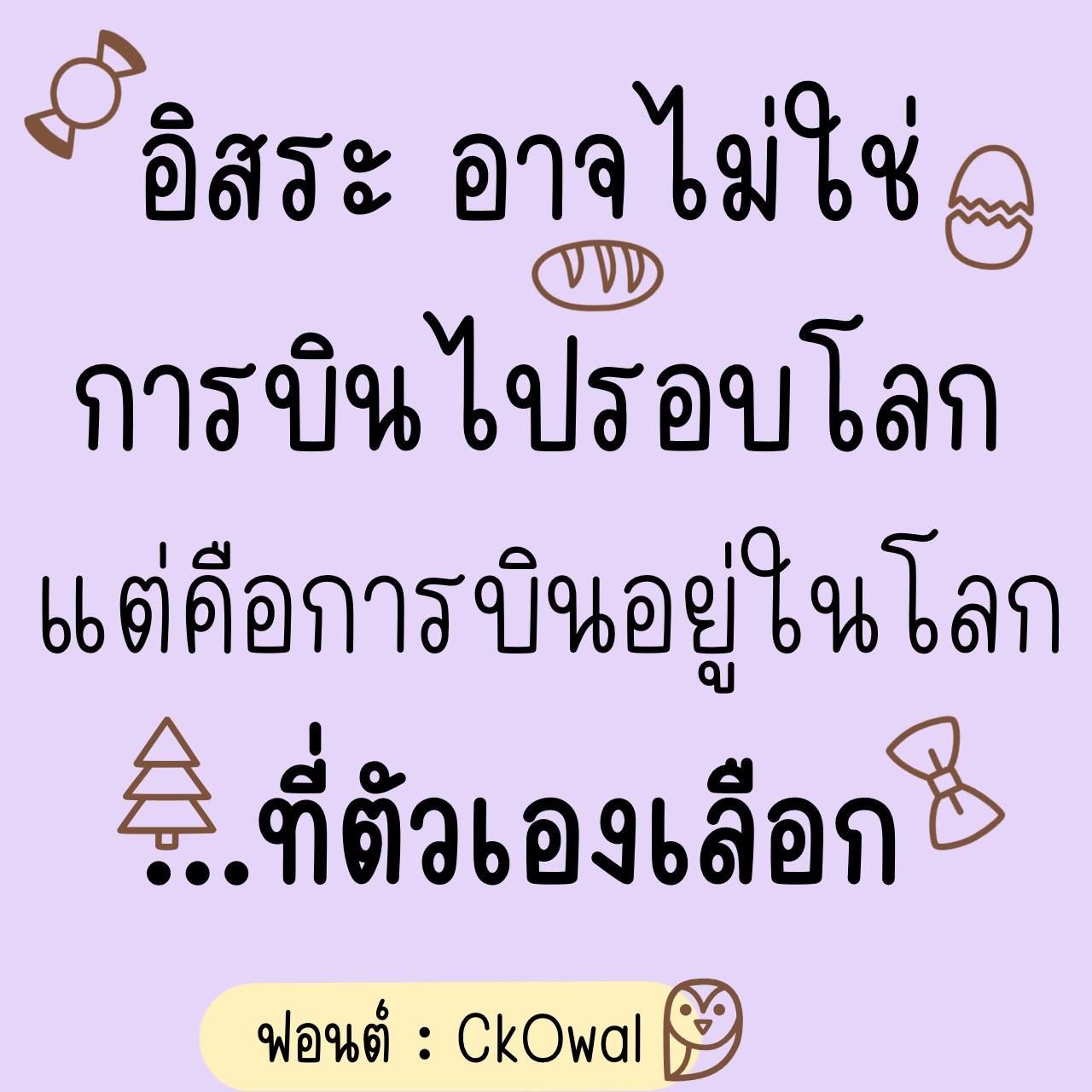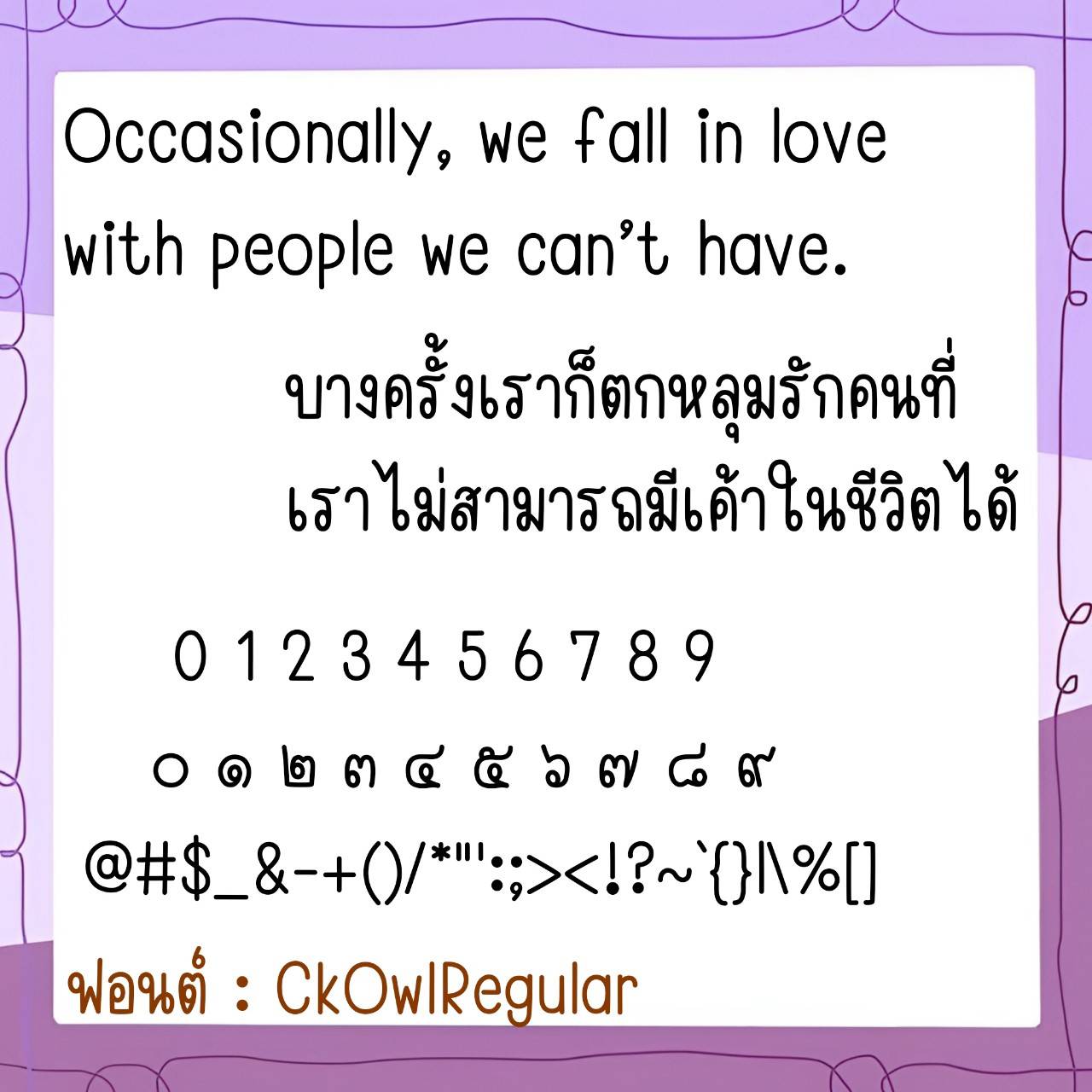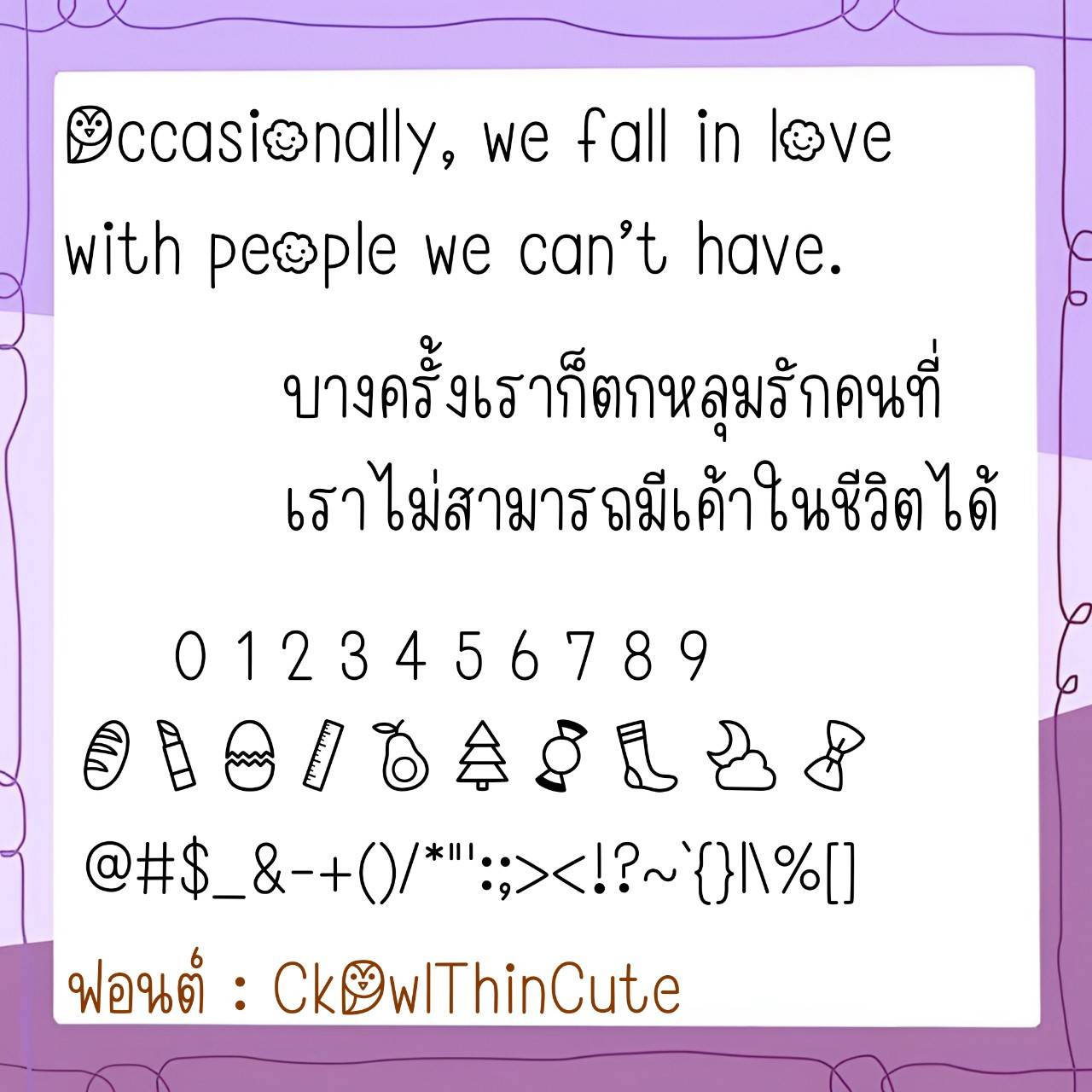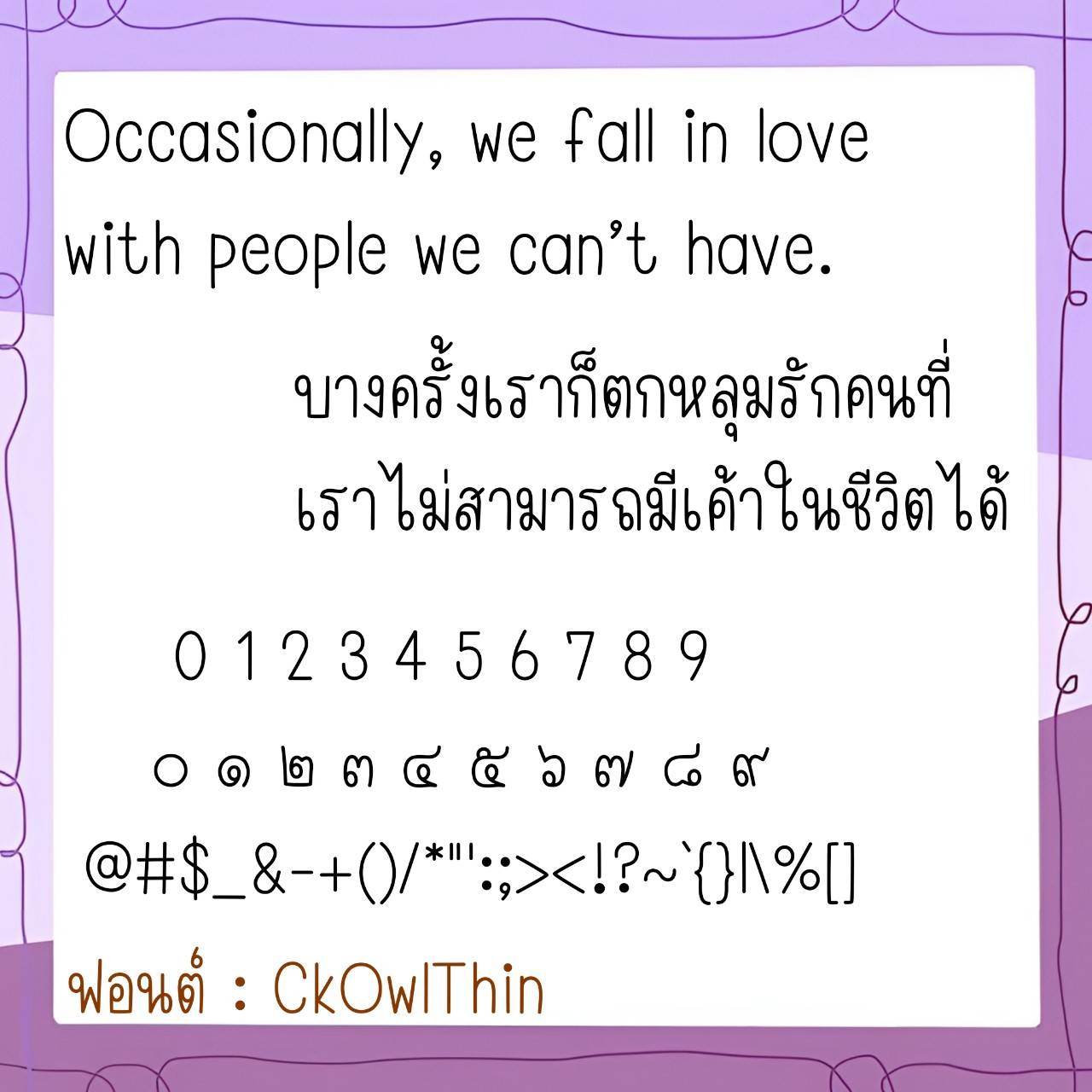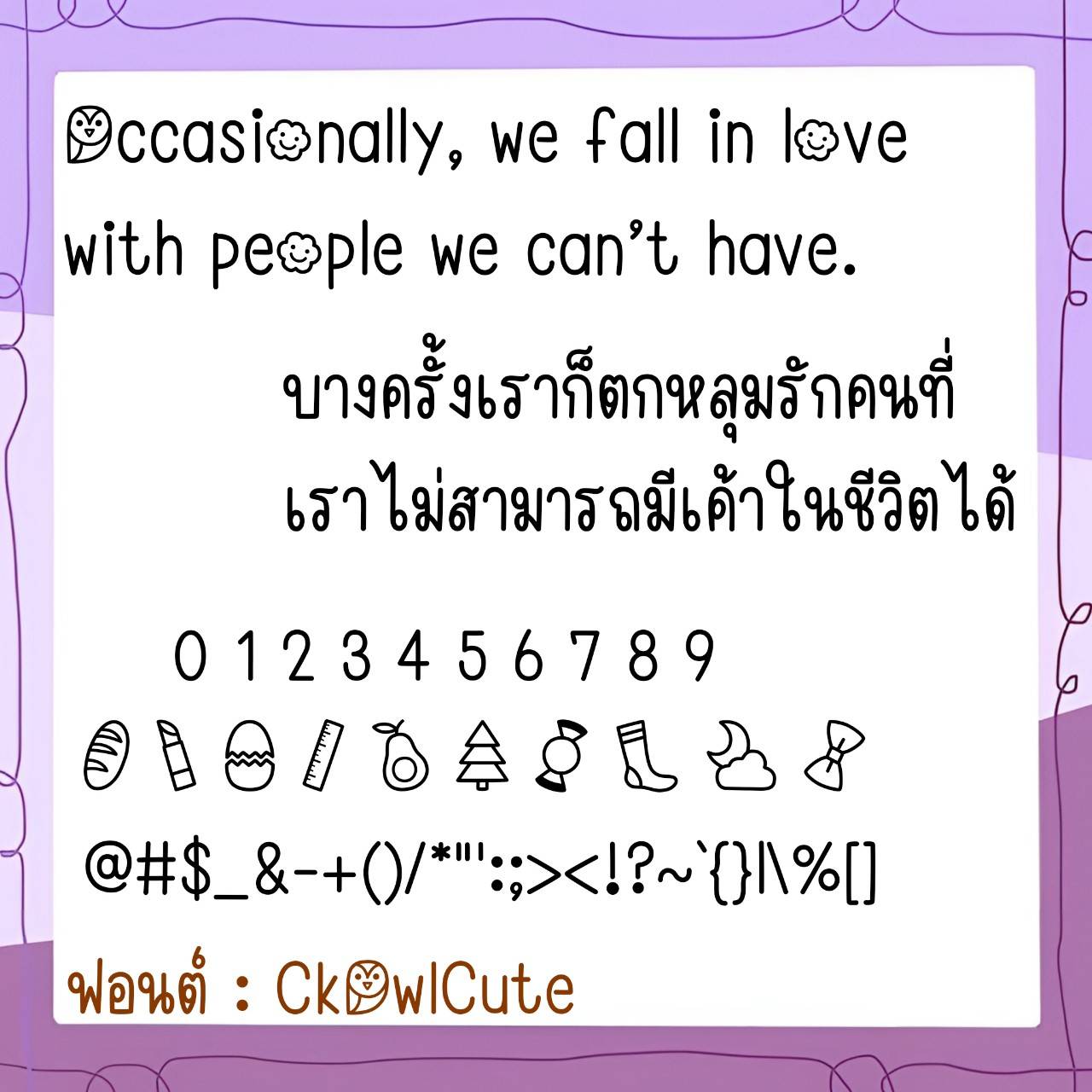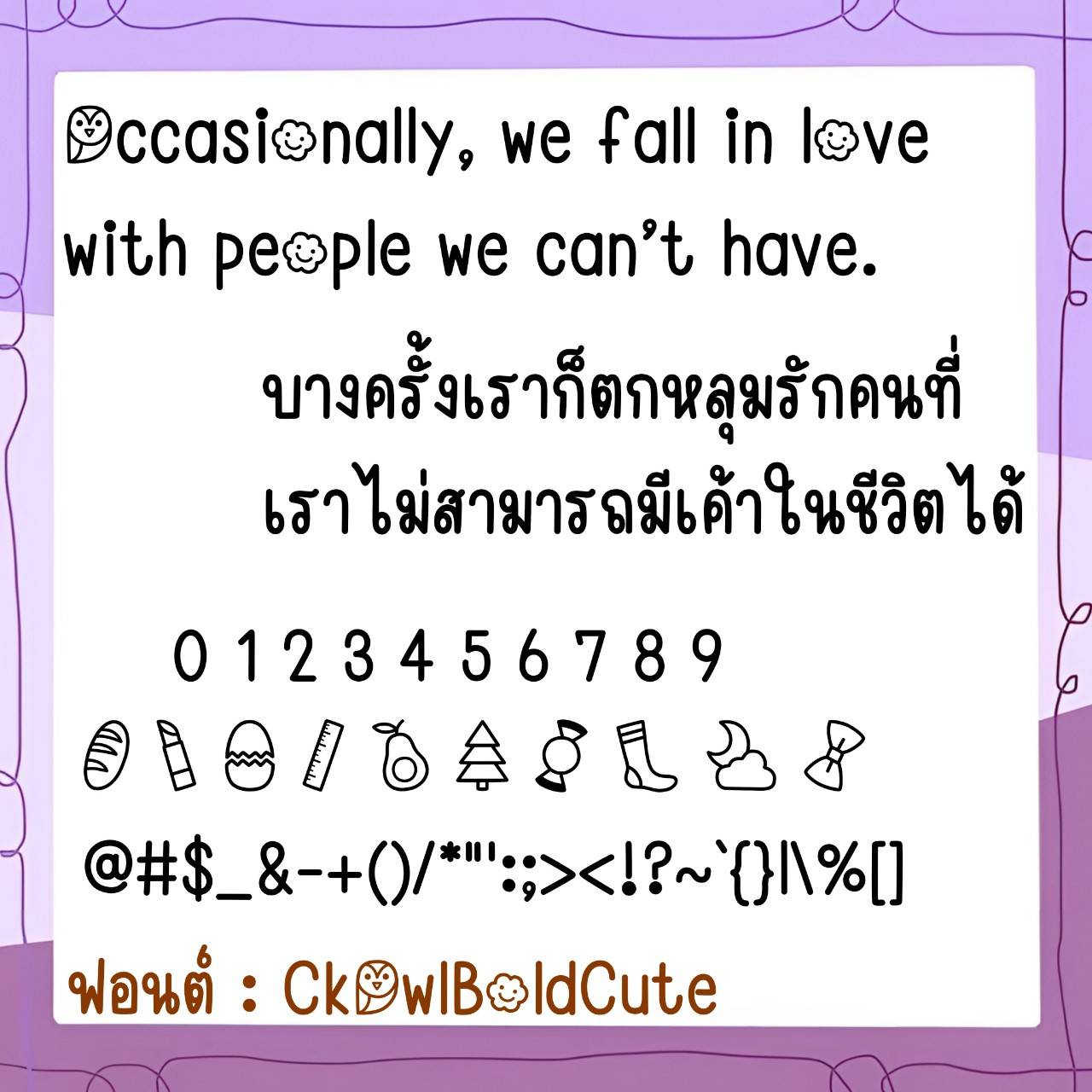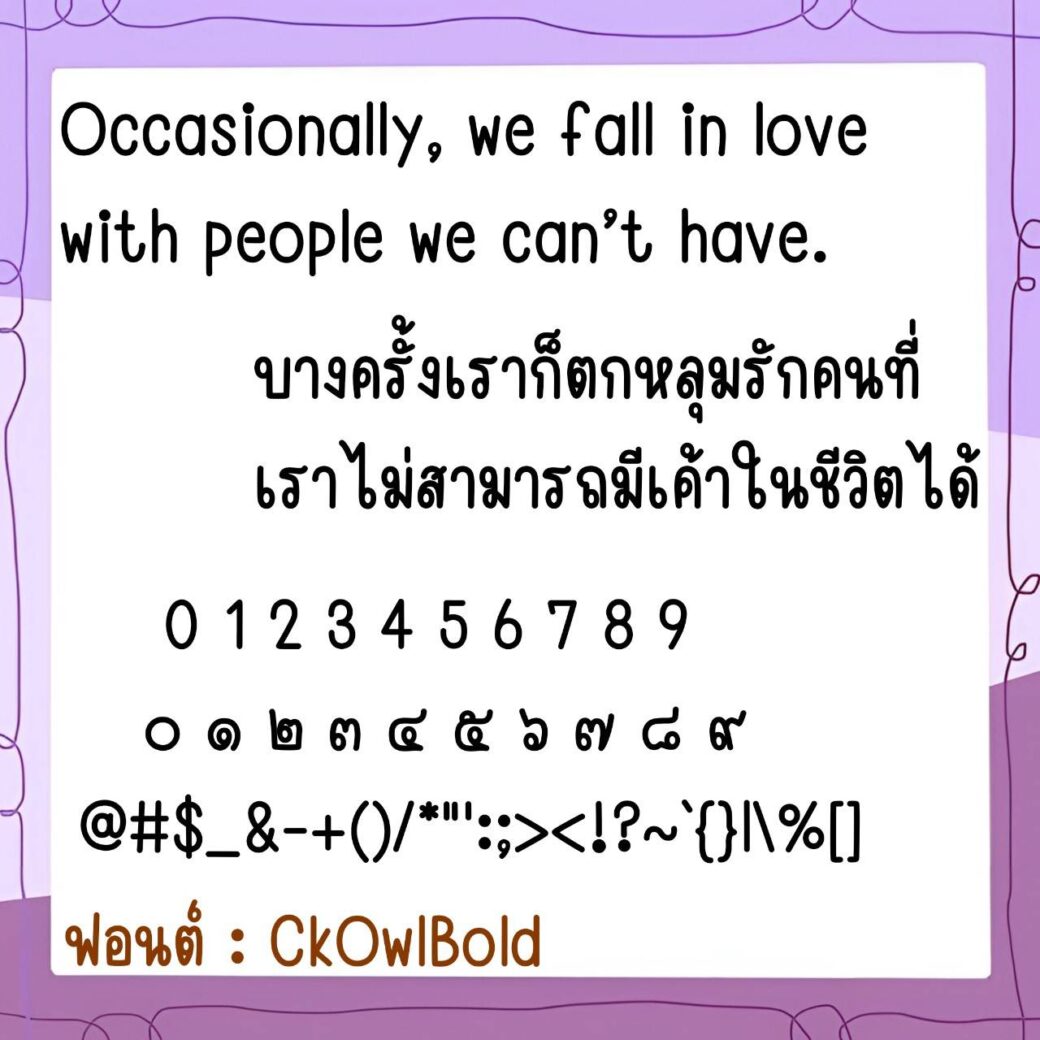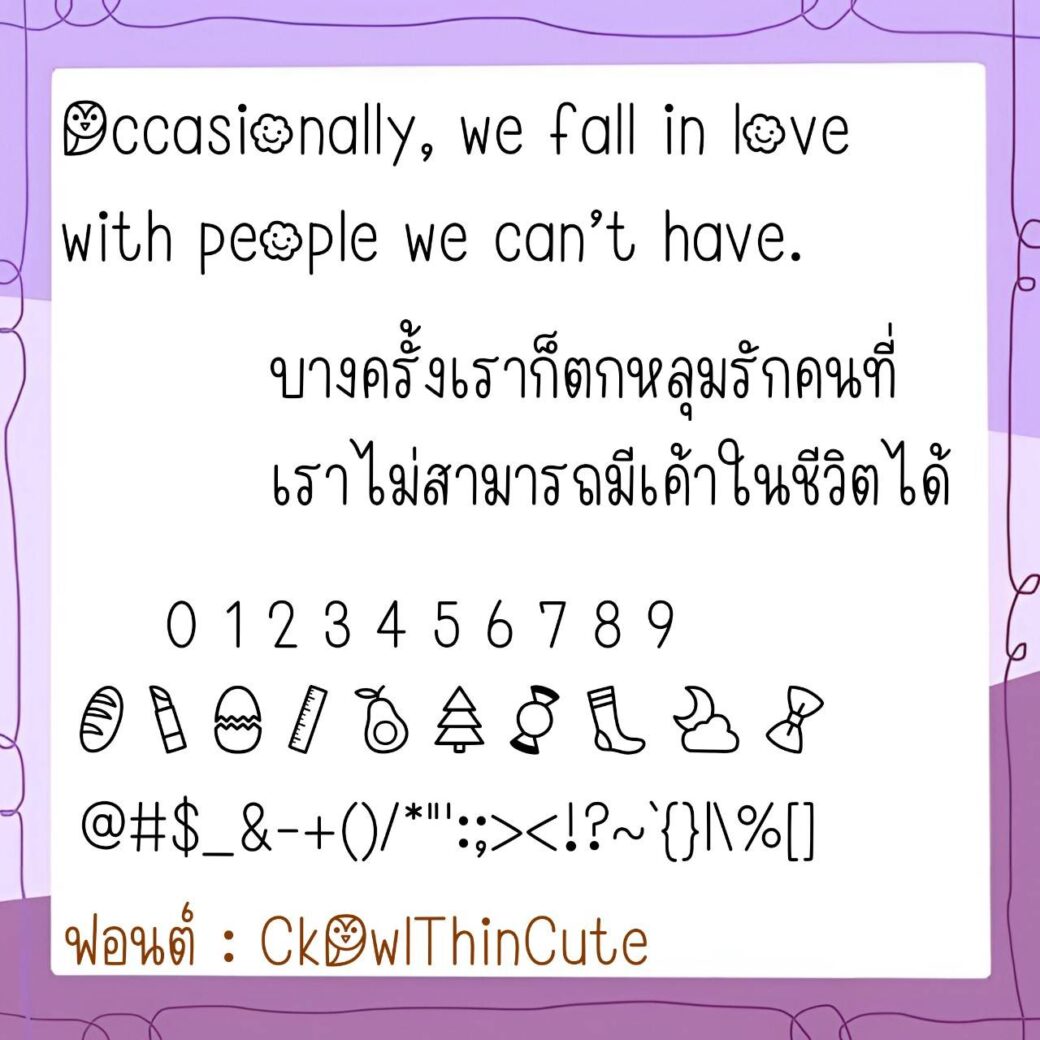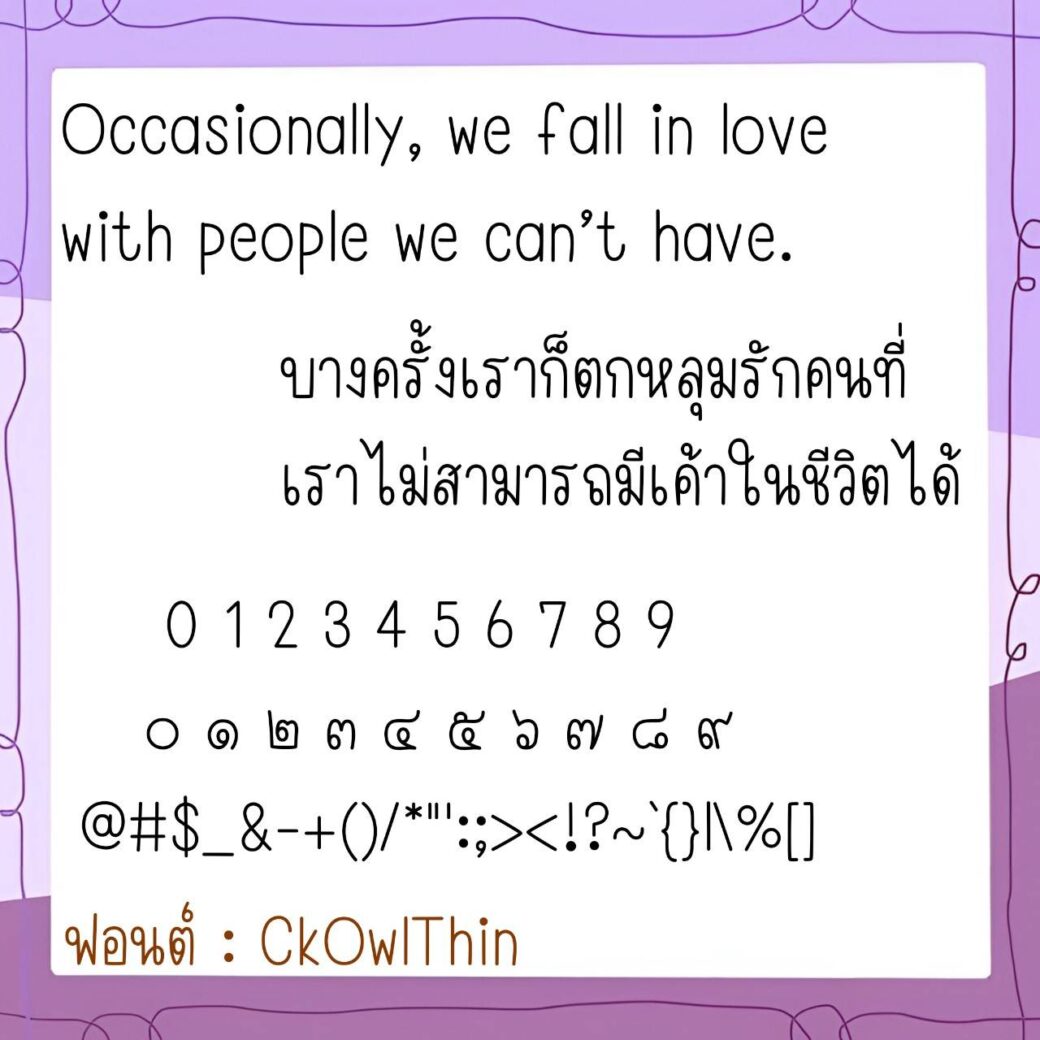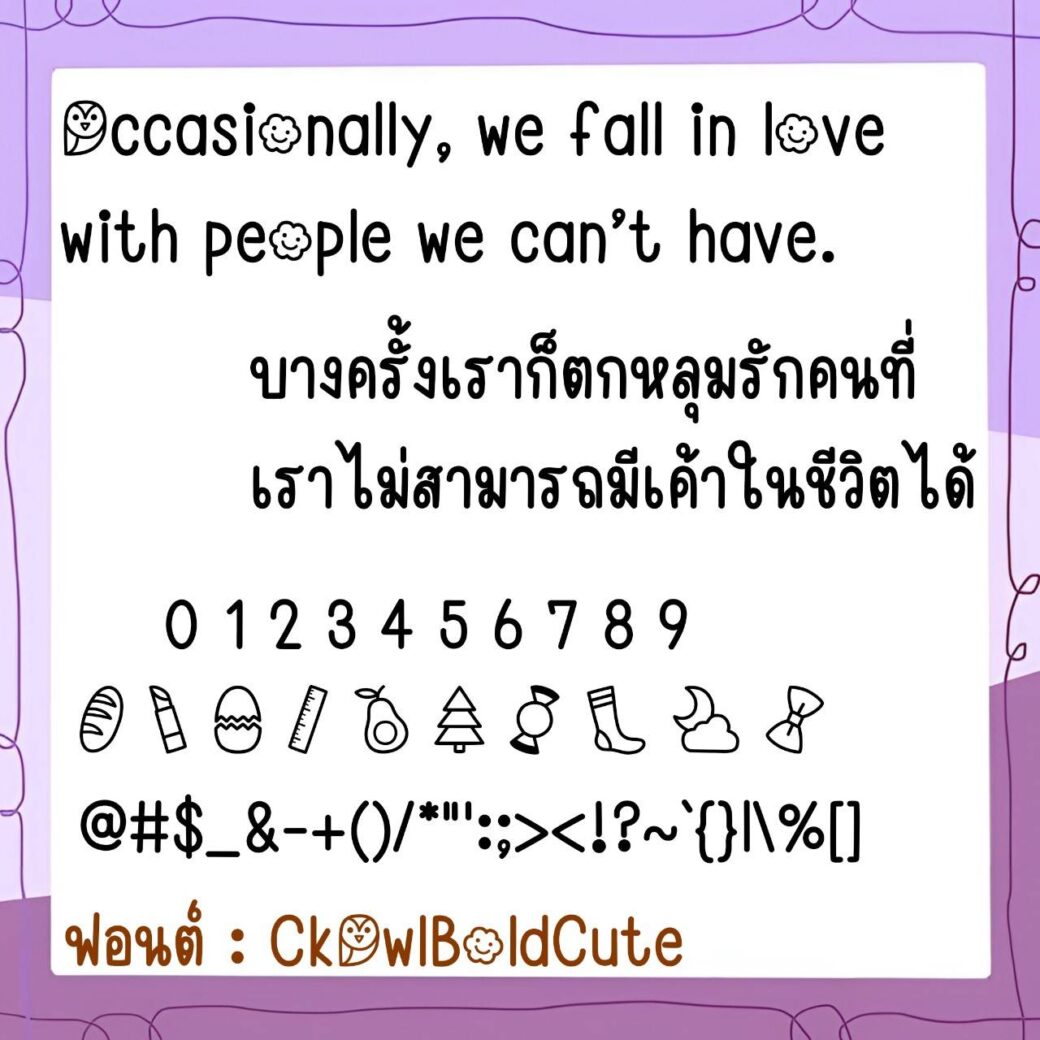
Font CkOwl
🔸 ฟอนต์ลายมือแนวหัวมนรี ขนาดฟอนต์กำลังพอดี ฟอนต์มีความกึ่งเรียบร้อยดูเป็นระเบียบ ดูอ่านง่ายน่าใช้งาน และยังมีไฟล์อิโมจิน่ารักๆ ที่ใช้แทนเลขไทยให้ด้วยค่ะ 🥰💙
🔹 The font is in the oval-shaped handwriting style. The font size is just right. The font is semi-neat and neat, looks neat, easy to read, and looks good to use. There is also a cute emoji file that can be used instead of Thai numbers. 🥰💙